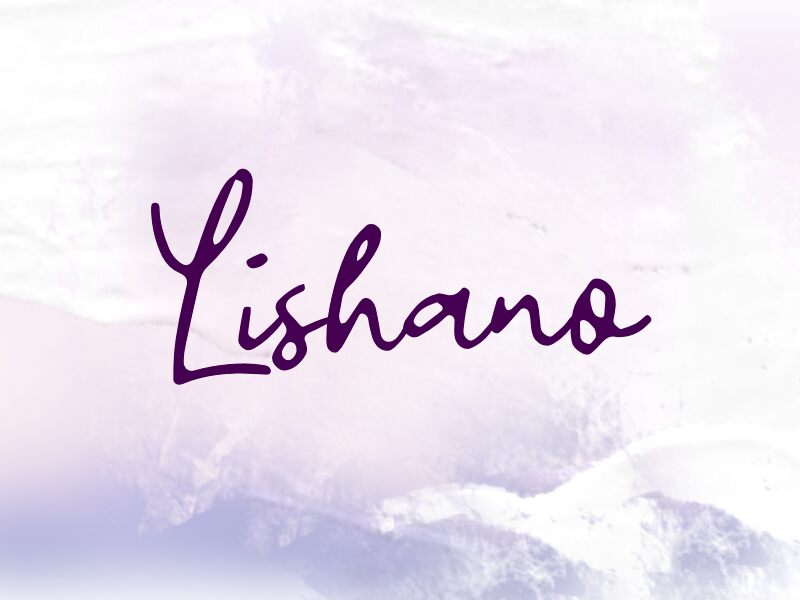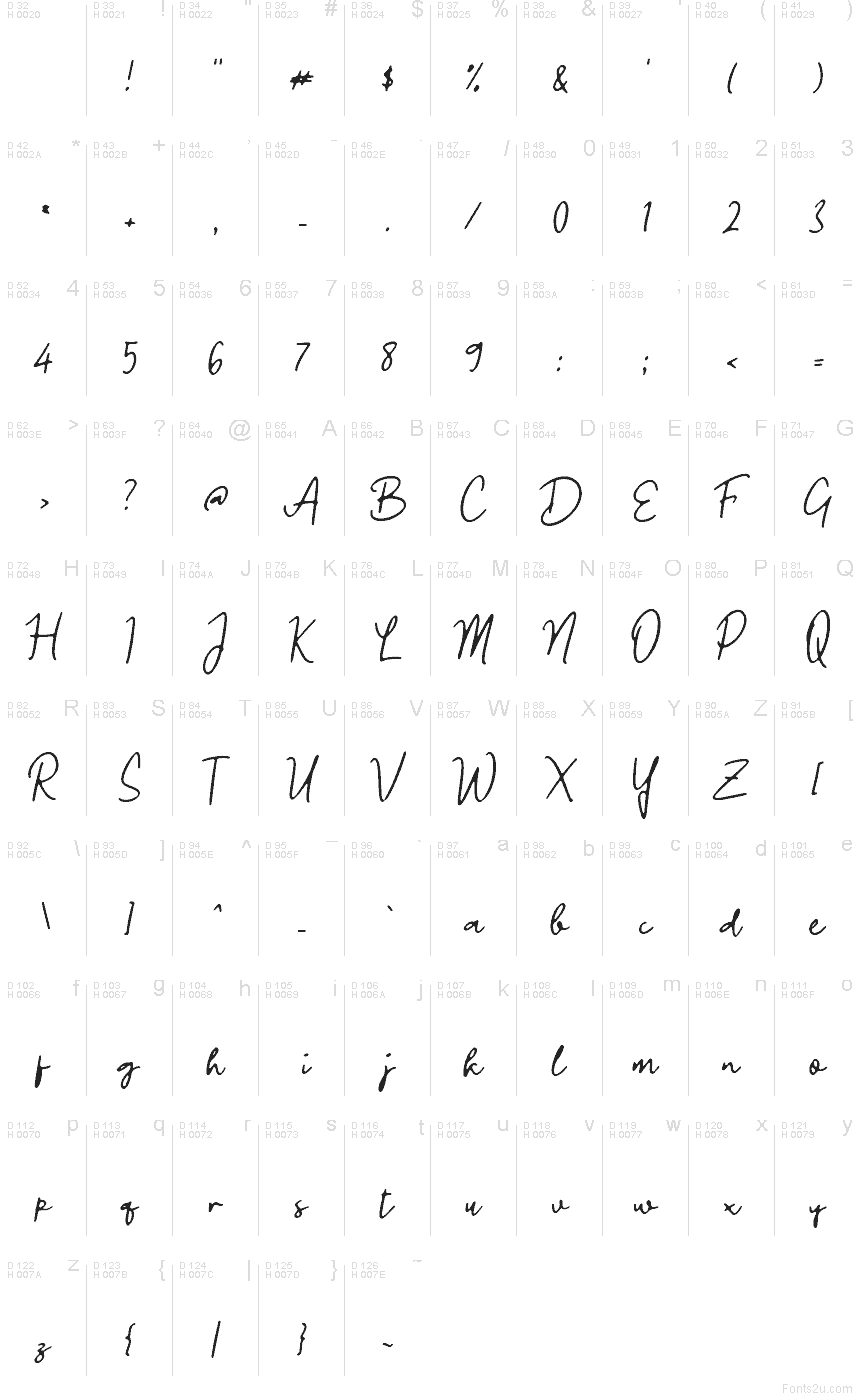
Lishano
Lishano di Wep è un font scritto a mano gratuito, caratterizzato da un ritmo libero, personale e da un accenno rétro. Le lettere giocano con tratti lunghi e sinuosi e giunzioni semplici, con una L iniziale alta e forme ovali strette che rendono il testo vivace senza risultare troppo elaborato.
È l'ideale per il branding di caffetterie, biglietti d'auguri, packaging beauty, post sui social e brevi titoli dove un tocco umano e autografo aiuta a definire lo stile. Essendo un font gratuito, funziona bene anche per titoli o iniziali in stile monogramma, poiché i suoi occhielli allungati e le curve rapide conferiscono a ogni parola un'autentica presenza scritta a mano.